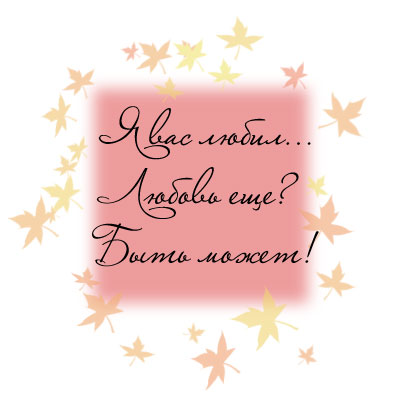
Шрифт - "Марианна"
Предлагаем Вашему вниманию изумительный рукописный шрифт под названием "Марианна".
не работает буква ы
Красивый шрифт! Но, у меня почему то нет букв "Ъ, Ы, Ь"
Хех, неплохо)0
Красивый
Классный романтический шрифт
Шрифт конечно обалденный, но вот у меня русский не поддерживает, только английский. Кто-то знает почему?
но думаю будет красиво
Шикарный шрифт *Q*
вау) крутой шрифт)
Изумительный шрифт *-* Спасибо ^^
красивейший шрифт)))
ПОТРЯСАЮЩИЙ ШРИФТ! МНЕ ОЧЕНЬ НРАВИТСЯ =)
Класс,спосибо!
классный шрифт)) нравится
Спасибо)) Очень красивый шрифт !
Нечто вроде Vera Crous. Красивый, спасибо!
Мне нравиться!*
ааее нравиться очень*
Неплохо совсем! Даже отлично!!! Спасибо!
Очень красивый шрифт)